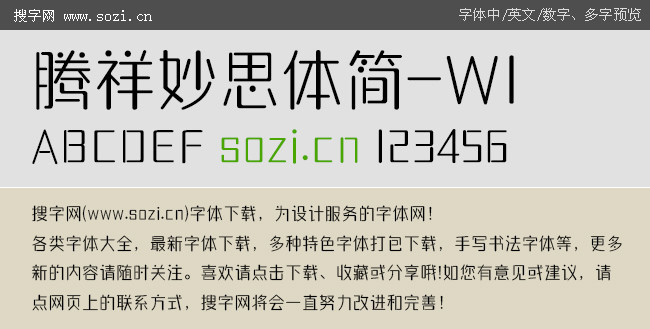
騰祥妙思體簡
搜字網(wǎng)提供一款騰祥妙思體簡中文藝術(shù)字體下載,騰祥妙思體簡是騰祥字庫最新推出的一款美術(shù)字體,妙思W1為系列字庫中最細(xì)一款,字形俊雅,風(fēng)格獨(dú)特。字形修長、筆畫設(shè)計巧妙、粗細(xì)搭配協(xié)調(diào)、筆畫凝練簡潔、整幅字給人以樸實(shí)無華,清新秀麗之感。字體可以廣泛應(yīng)用于印刷出版、包裝設(shè)計、廣告設(shè)計、網(wǎng)頁設(shè)計等領(lǐng)域。